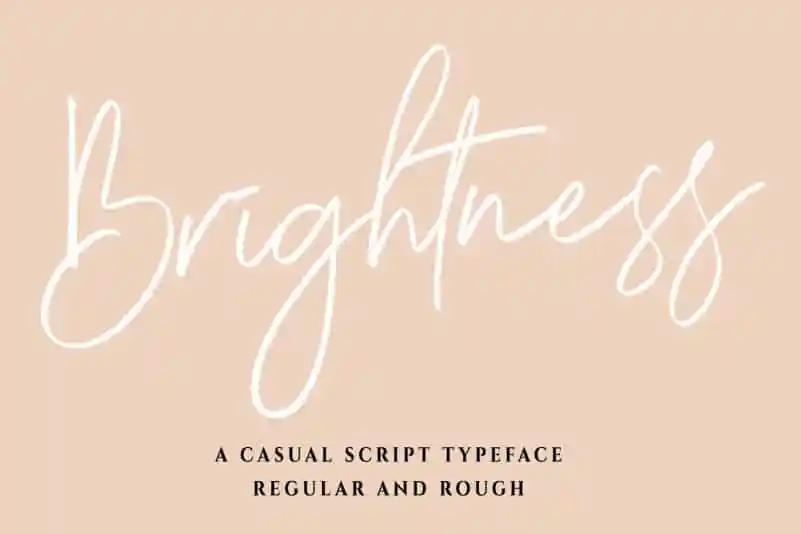
Brightness Script Font – Download Grátis
A Brightness Script Font é uma escolha perfeita para projetos de luxo, seja no design de cartões de aniversário ou assinaturas elegantes, logotipos sofisticados, citações impressas, cartazes de feliz aniversário, cabeçalhos de mídias sociais e embalagens de produtos. Suave e fluida, ela transmite sofisticação e criatividade em qualquer aplicação. Ideal para projetos que exigem uma escrita autêntica e elegante, esta fonte é a escolha perfeita para quem valoriza estilos criativos no design. Ela é um trunfo na sua paleta de ferramentas de design, garantindo sempre um toque único em seus projetos de marca ou comunicação visual.